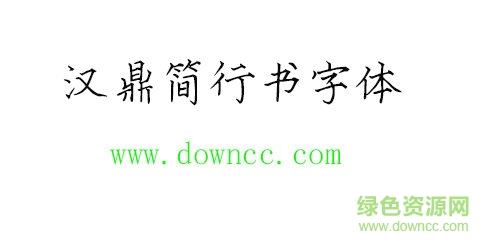
漢鼎簡行書是一款非常適合設(shè)計(jì)行業(yè)的字體,閑暇時(shí)模仿字的寫法還可以幫你練出一手好字哦,這也是書法家們在創(chuàng)作時(shí)必選的字體之一,其文字描述非常具有特色,如果你想創(chuàng)作書法作品,不妨使用一下該字體哦,喜歡的朋友趕緊來綠色資源網(wǎng)下載吧!
1.筆畫端正均勻,筆形清秀、舒展,結(jié)構(gòu)寬博;
2.橫豎筆畫粗細(xì)差別不明顯,可作為雜志和書籍的正文首選字體,